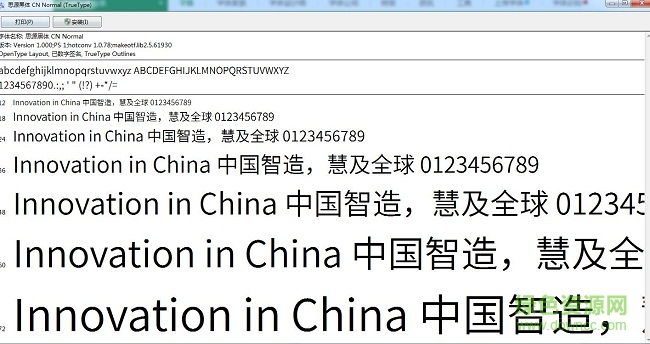
sourcehansanscn-normal-gbpc-euc-h常規(guī)字體又叫思源黑體cn normal字體,是一款由Adobe公司推出的高品質(zhì)黑體字體,設(shè)計精致,優(yōu)雅大氣,顯示效果優(yōu)秀,歡迎大家免費下載使用!
黑體又可細(xì)分為:粗黑、超粗黑(特黑)、大黑、細(xì)黑、美黑、宋黑、水黑、藝黑、氈筆黑、平黑等類型。
1.它渾厚有力,樸素大方和引人注目,很適于標(biāo)語、標(biāo)題,使人重視;
2.方頭方尾,點、撇、捺、挑、勾也都是方的,所以又叫方體;
3.它結(jié)構(gòu)嚴(yán)謹(jǐn),筆劃單純,所以也常作為初學(xué)美術(shù)字練習(xí)的一種字體。